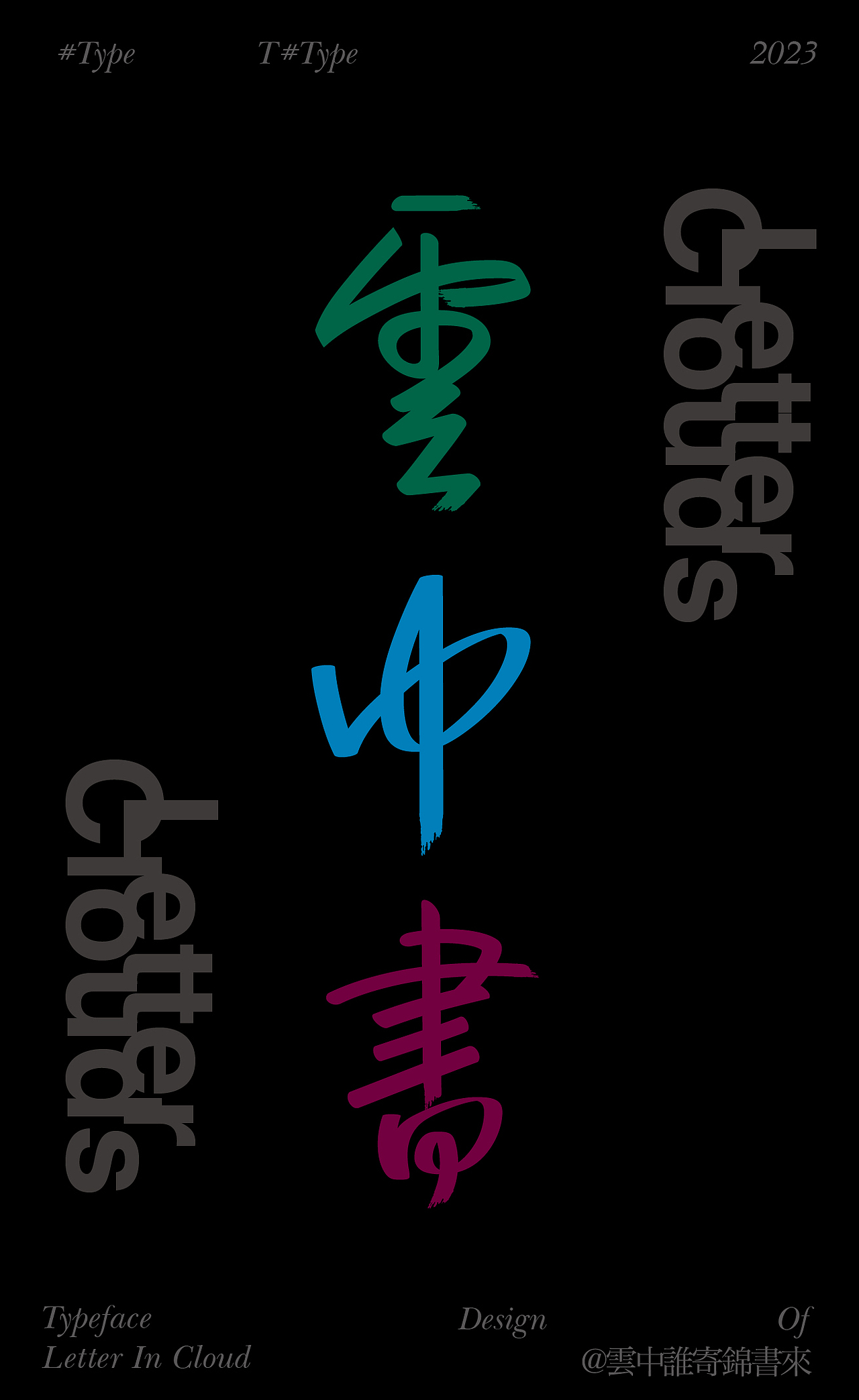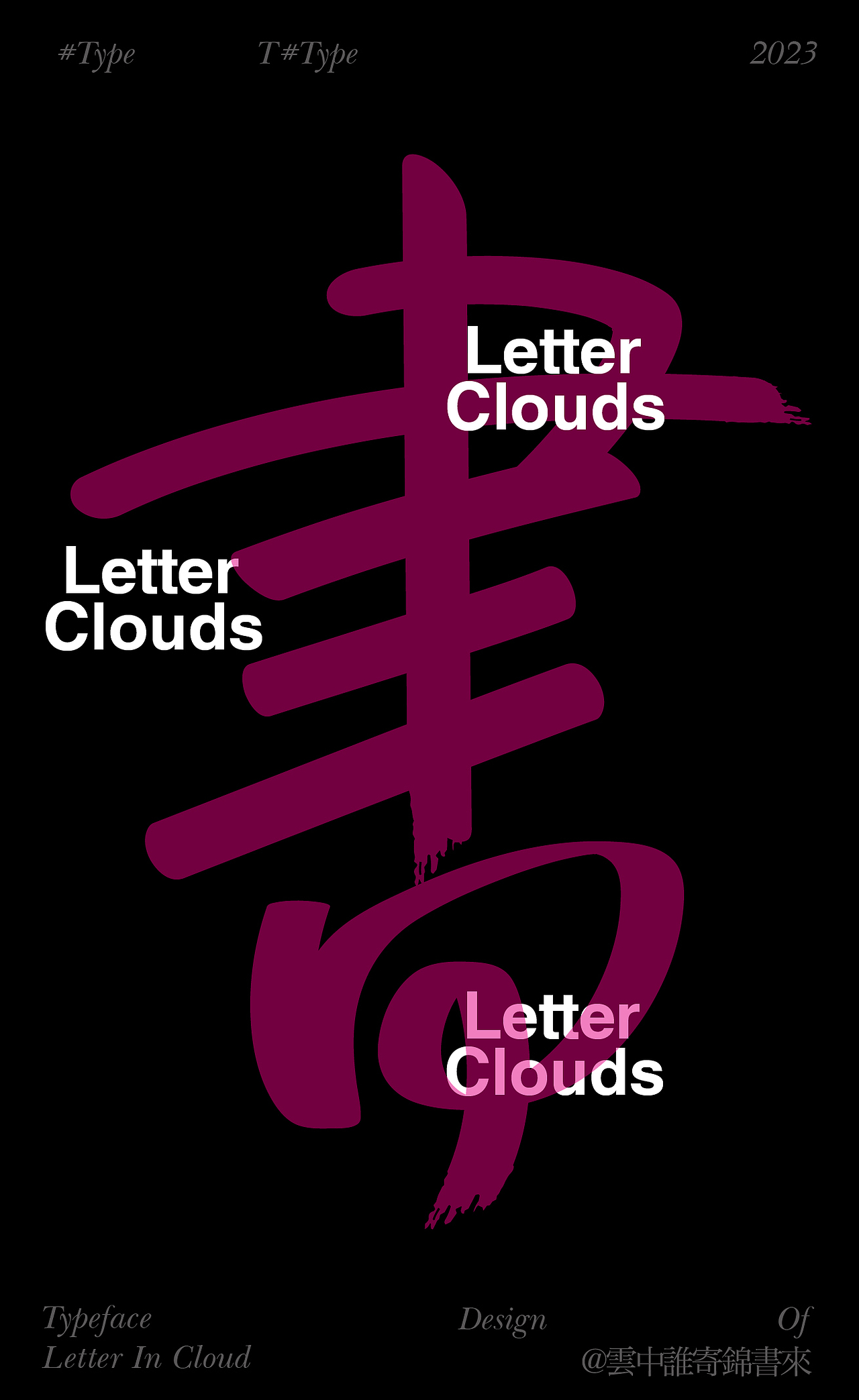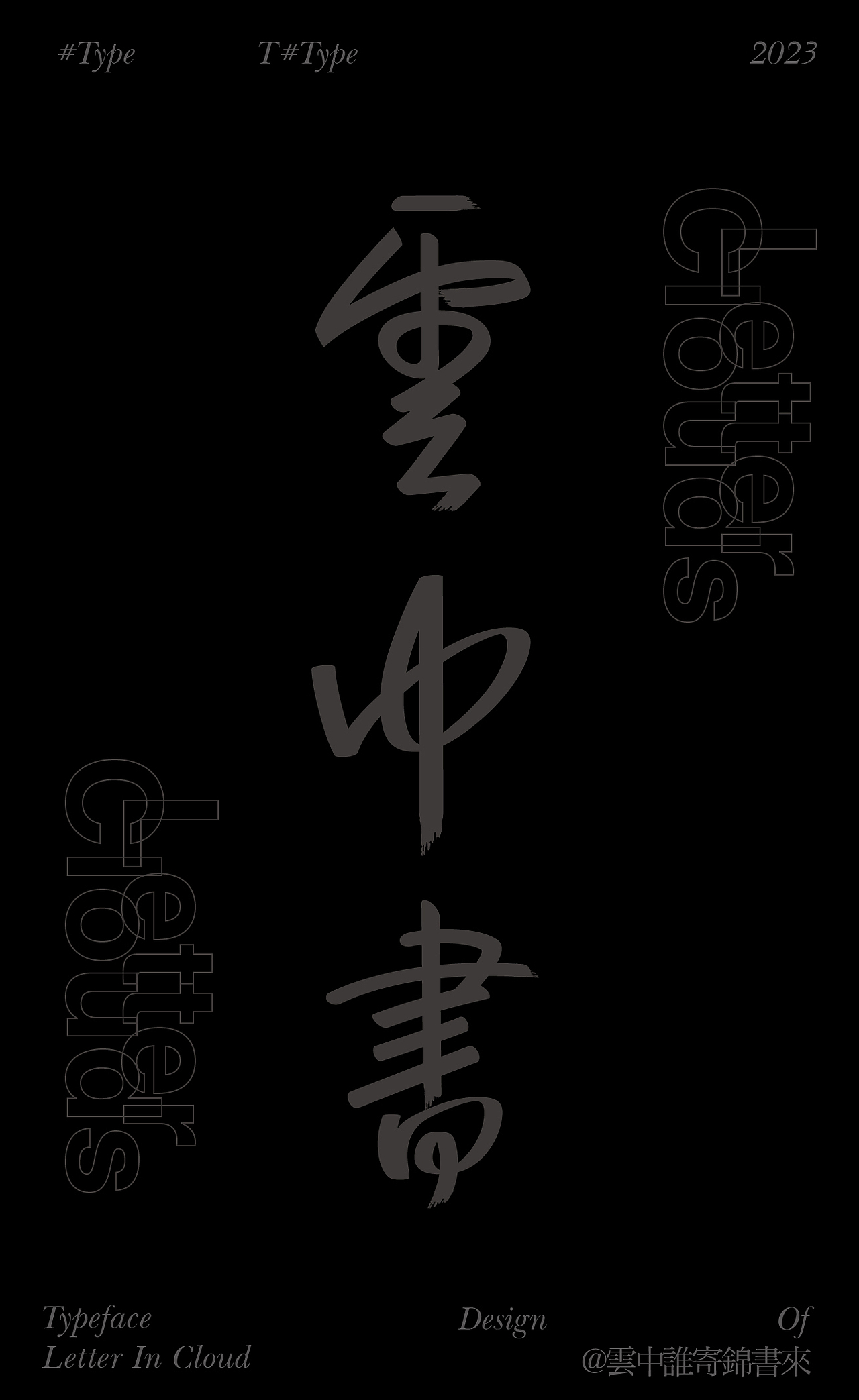
字体|云中谁寄锦书来
源于李清照的那句“云中谁寄锦书来”。原是作者表达对丈夫的思念之情,亦或是被后人拿来抒发知音难觅的孤独之感,与其同出于此的另外一句广为流传:“才下眉头,却上心头。”
手写感汉字的人文风与机械感字母的工业化风格交织,
互为云与书的关系,两者亦书亦云。
“红藕香残玉簟秋。轻解罗裳,独上兰舟。云中谁寄锦书来?雁字回时,月满西楼。
花自飘零水自流。一种相思,两处闲愁。此情无计可消除,才下眉头,却上心头。”